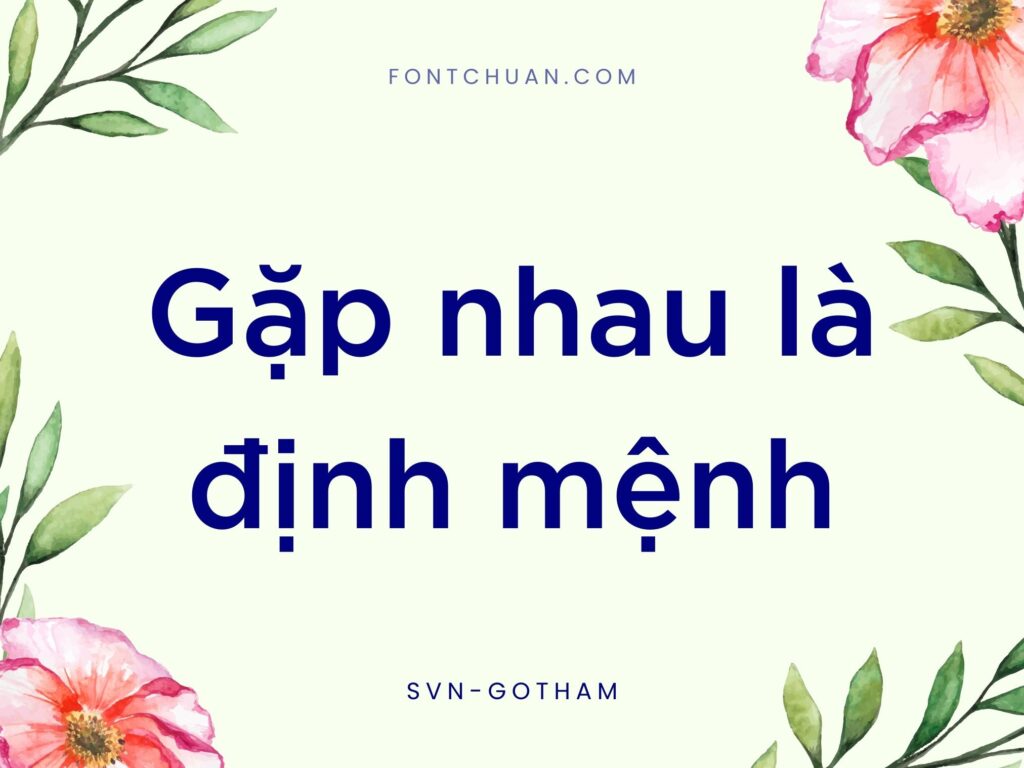
Font SVN Gotham Sử Dụng Trong Logo Tiktok Việt Hóa
Tác giả Font: Tobias Frere-Jones
Font SVN Gotham là phiên bản Việt hóa của kiểu chữ Gotham, được thực hiện bởi Styleno.1 Fonts. Gotham là một kiểu chữ sans-serif hình học được thiết kế bởi Tobias Frere-Jones vào năm 2000 và phát hành qua công ty Hoefler & Co. Font này nổi bật với thiết kế sạch sẽ, hiện đại và dễ đọc, đã được sử dụng rộng rãi trong nhiều lĩnh vực thiết kế và thương hiệu nổi tiếng.
SVN Gotham lý tưởng cho các dự án thiết kế yêu cầu sự chuyên nghiệp và hiện đại, như thiết kế logo, tiêu đề, bao bì sản phẩm và các ấn phẩm quảng cáo. Các ngành nghề như quảng cáo, công nghệ và giáo dục có thể tận dụng font này để tạo điểm nhấn trong thiết kế. Ngoài ra, font cũng thích hợp cho các sự kiện như Tết, Giáng sinh, Valentine và các lễ hội khác.